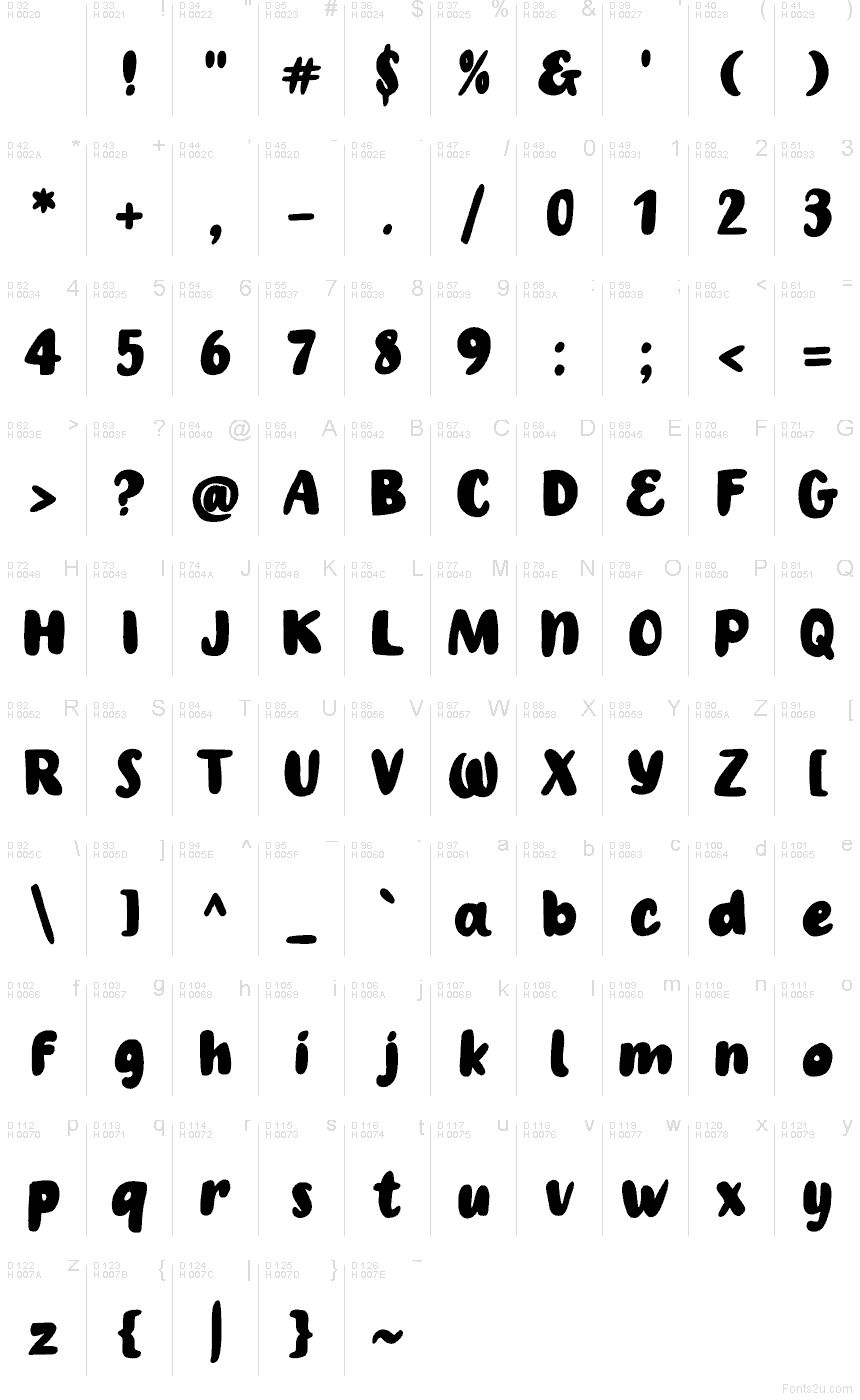
Handcrit هو خط عرض كرتوني مجاني يتميز بأشكال دائرية مرسومة يدوياً ومنحنيات ناعمة وممتلئة. تبدو الحروف مدمجة وودودة، مع حواف انسيابية وإيقاع غير منتظم قليلاً يمنح المجموعة طابعاً عفوياً مرسوماً باليد.
يعد Handcrit خياراً مثالياً لملصقات الأطفال، وعناوين القصص المصورة، والملصقات اللاصقة، ورسومات وسائل التواصل الاجتماعي، ونصوص الشعارات القصيرة التي تتطلب طابعاً دائرياً غير رسمي. تعمل أشكاله الناعمة بشكل رائع مع العناوين المبهجة، وملصقات الأعمال اليدوية، وتفاصيل التغليف، ولافتات الفعاليات، لأن تصميم الحروف يجعل النص يبدو مريحاً وودوداً للعين.